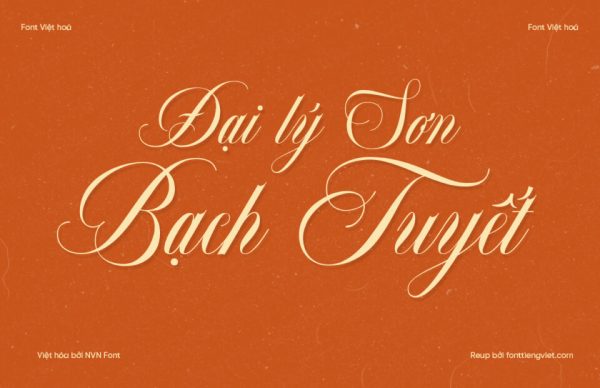
Giới thiệu bộ Font Việt hóa NVN Cameo Sweet
Trong thế giới đồ họa hiện đại, việc lựa chọn một Font Miễn Phí có tính thẩm mỹ cao luôn là ưu tiên hàng đầu của các nhà sáng tạo. Font Việt hóa NVN Cameo Sweet là một tác phẩm nghệ thuật chữ viết mang phong cách calligraphy hiện đại, nổi bật với những đường nét mềm mại và uyển chuyển. Bộ phông chữ này không chỉ đơn thuần là công cụ soạn thảo mà còn là linh hồn cho các bản thiết kế mang hơi hướng lãng mạn, trẻ trung. Với sự chăm chút kỹ lưỡng trong quá trình Việt hóa, người dùng có thể hoàn toàn yên tâm về khả năng hiển thị tiếng Việt chuẩn xác, không gặp lỗi dấu hay khoảng cách chữ.
Đặc điểm nổi bật của Font Việt hóa NVN Cameo Sweet
Điểm thu hút lớn nhất của Font Việt hóa NVN Cameo Sweet chính là sự kết hợp tinh tế giữa các nét thanh và nét đậm. Các ký tự được thiết kế với độ cong tự nhiên, tạo cảm giác như được viết tay bởi những nghệ nhân chuyên nghiệp. Bộ font này đi kèm với hệ thống ký tự thay thế phong phú, giúp bạn dễ dàng tùy biến các đuôi chữ để tạo điểm nhấn khác biệt. Đây là lựa chọn hoàn hảo cho các bạn học sinh, sinh viên khi làm thiệp mừng, trang trí báo tường điện tử hay thiết kế các ấn phẩm quà tặng dành cho thầy cô và bạn bè.
Ứng dụng thực tế và cách sử dụng hiệu quả
Font Việt hóa NVN Cameo Sweet cực kỳ đa năng trong nhiều lĩnh vực thiết kế khác nhau. Bạn có thể sử dụng nó để làm tiêu đề cho các trang blog cá nhân, thiết kế logo thương hiệu handmade hoặc trình bày các câu trích dẫn truyền cảm hứng trên mạng xã hội. Để đạt hiệu quả thị giác tốt nhất, hãy kết hợp font chữ này với các tông màu pastel nhẹ nhàng hoặc phông nền tối giản. Điều này giúp các đường nét uốn lượn của bộ chữ trở nên nổi bật và sang trọng hơn bao giờ hết.
Kết luận về bộ phông chữ NVN Cameo Sweet